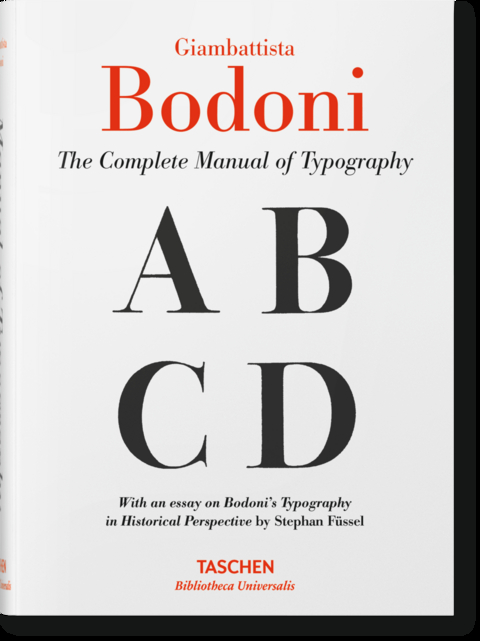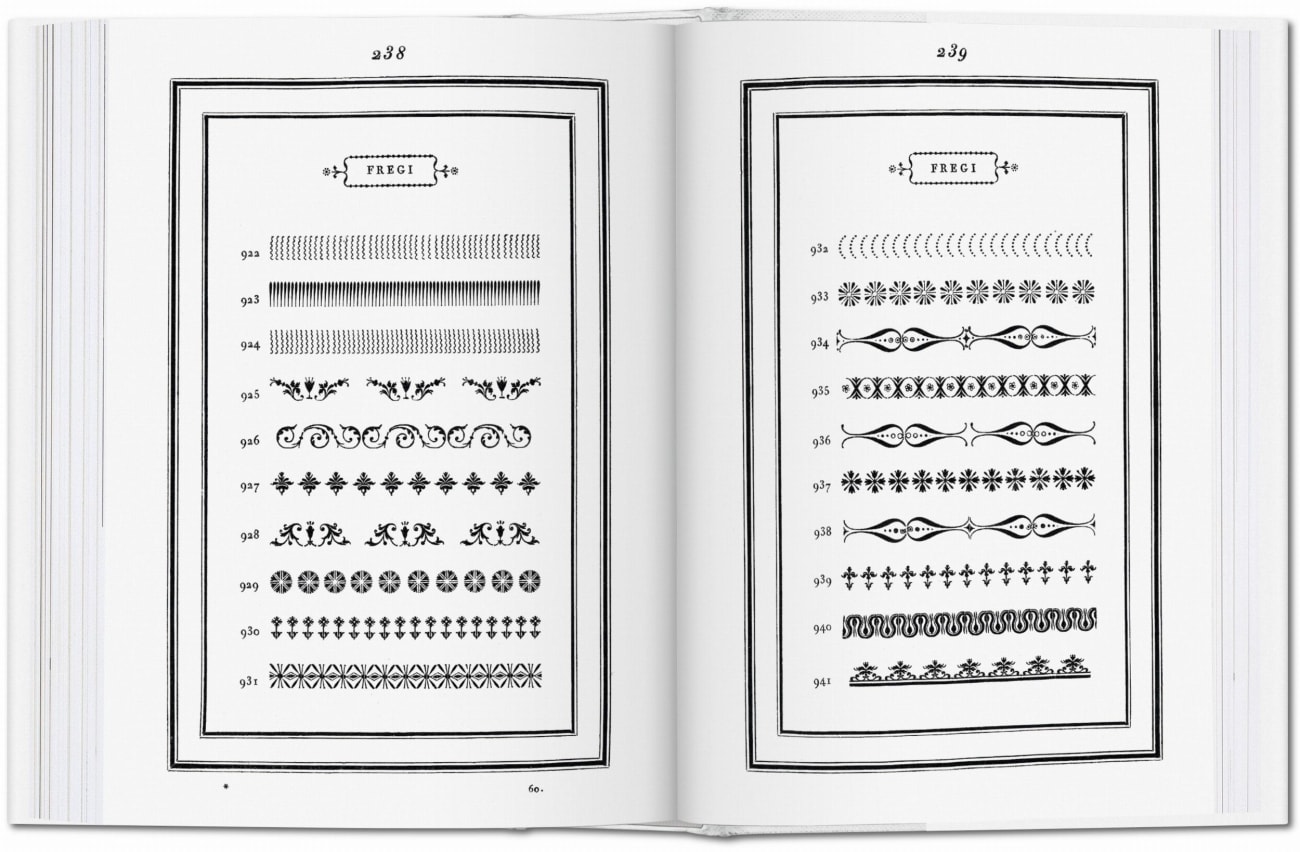
Giambattista Bodoni. Das vollständige Handbuch der Typografie
Auch rund 200 Jahre nach seinem Tod bestechen die von Giambattista Bodoni entworfenen Antiquaschriften durch kühle Eleganz und klassizistische Formstrenge. Die Bilanz seines Lebenswerkes, das Manuale tipografico von 1818, unterstreicht Bodonis herausragende Bedeutung für den Buchdruck. Nachdruck eines Klassikers der Typografie.
lt;p>Giambattista Bodoni (1740-1813), Schriftenentwickler, Stempelschneider und offizieller Buchdrucker des Herzogs von Parma, war ein begnadeter Graveur und besessener Perfektionist, der selbst seine Druckerschwärze noch speziell nachbehandelte, um ein perfektes Druckbild zu erzielen. In die Geschichte der Buchkunst eingeschrieben aber hat er sich mit seinen eleganten klassizistischen Antiquaschriften, die auch heute noch in zahllosen Variationen und Neuinterpretationen Verwendung finden. Bodonis Schriften weisen einen beispiellosen Grad an technischer Raffinesse auf und sind von zeitloser Schönheit. Das 1818 posthum erschienene Manuale tipografico, ein Muster- und Lehrbuch der Typografie und Resümee eines ungeheuren Lebenswerkes, stellt eine der größten typografischen Leistungen der Geschichte dar.Wie das Original enthält dieser vollständige Nachdruck 142 Sätze mit Antiquaschriften von einzigartiger Eleganz samt korrespondierender Kursiven, eine große Auswahl an typografischen Ornamenten und Schmuckelementen sowie Schriftproben russischer, griechischer und zahlreicher exotischer Schriften. Wer sich für Schrift und Sprache begeistert, kommt an diesem Klassiker nicht vorbei.